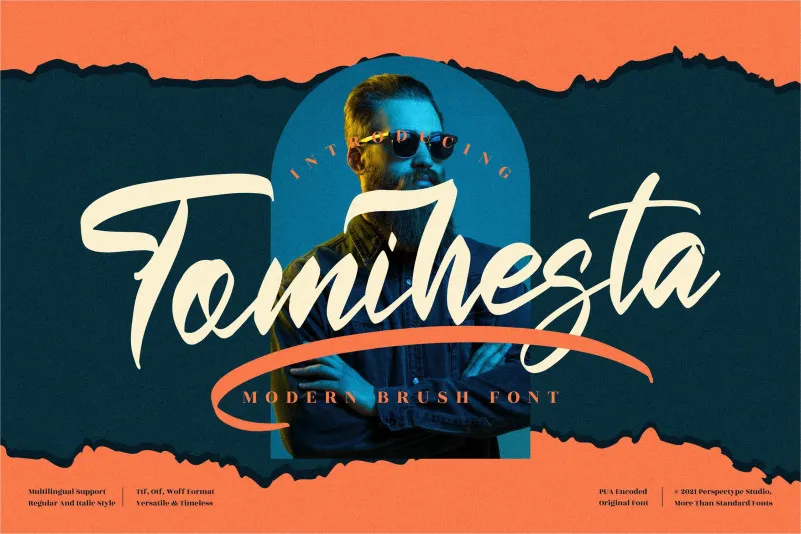
Tomihesta Font – Download Grátis
Esta é uma fonte Brush Script que captura a essência moderna e atrevida do estilete. Ela foi cuidadosamente moldada para ser perfeita na mão, com detalhes extremamente finos e detalhados. Seja ela o tema de um logotipo, texto ou até mesmo gráficos de ilustração, essa fonte é certamente uma aquisição valiosa para qualquer biblioteca de fontes. Ela está codificada PUA, o que significa que você poderá acessar facilmente todos os símbolos e swashes desta fonte. Aqui está algo mais sobre a fonte: esta é uma opção perfeita para quem procura um estilo bold e delicado. O designer perspectype soube capturar exatamente como esse estilo deve ser, criando uma combinação única de modernidade e sutileza que faz com que essa font seja tão única e valiosa em sua biblioteca de fontes. Sem dúvida, essa é uma escolha que merece o seu espaço no armário de recursos gráficos.